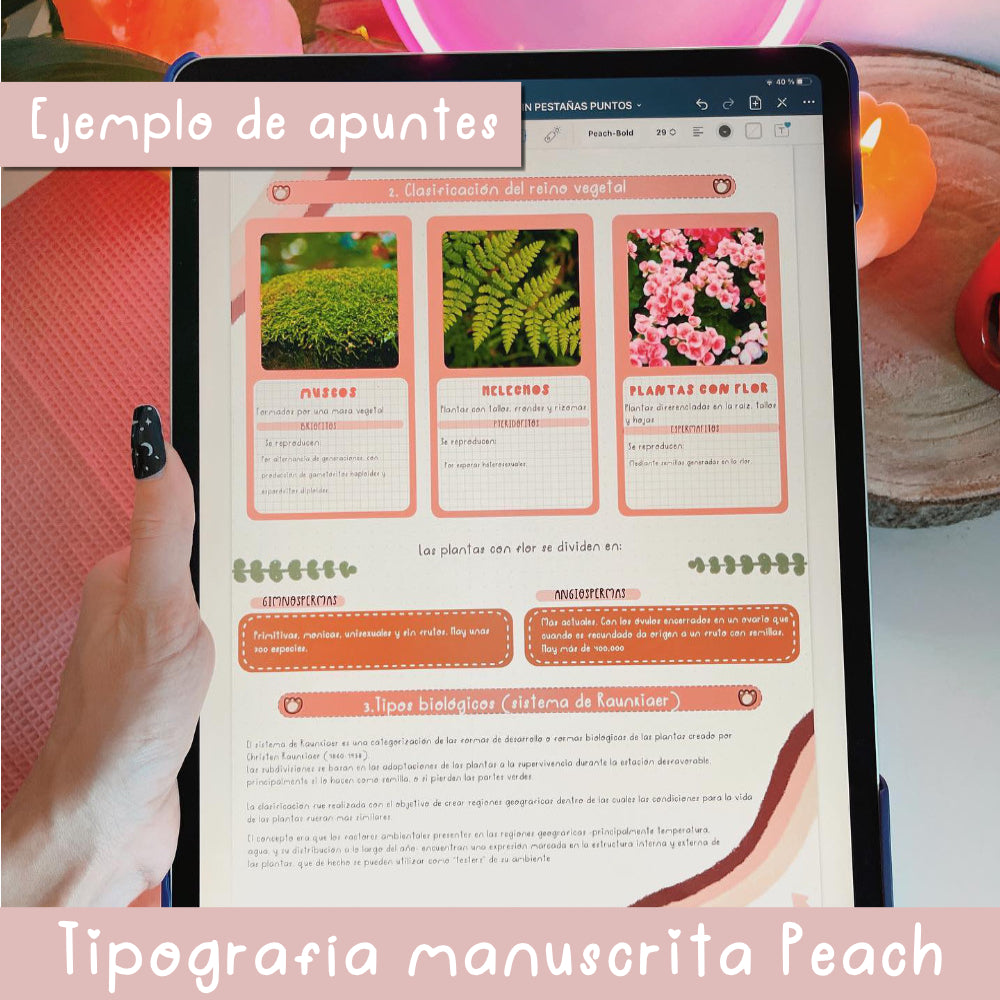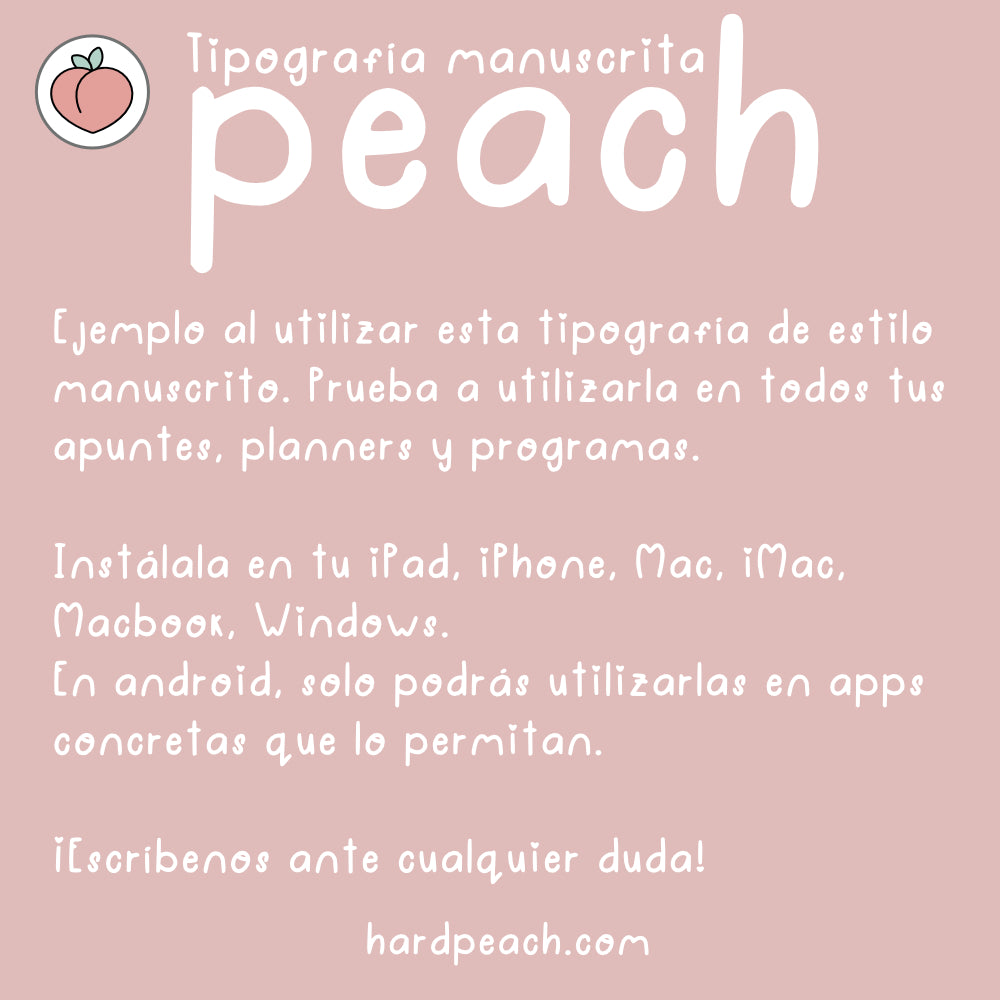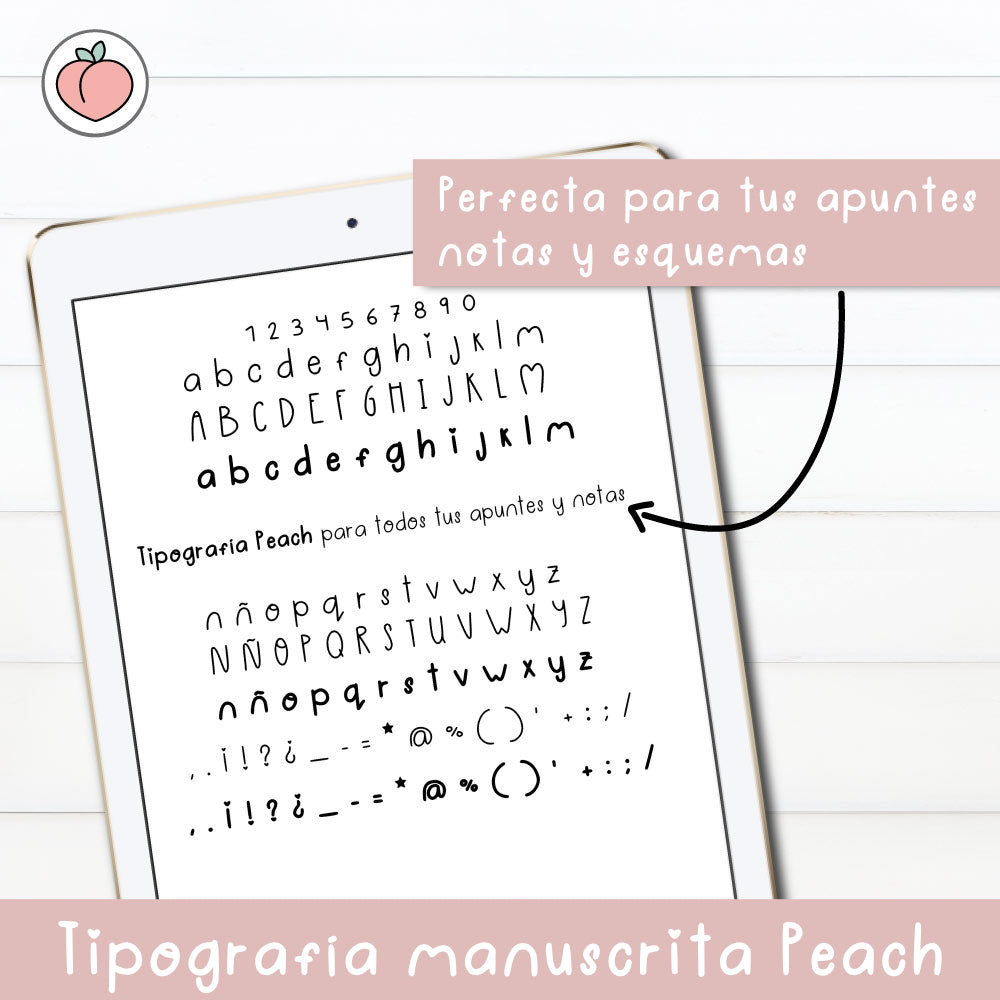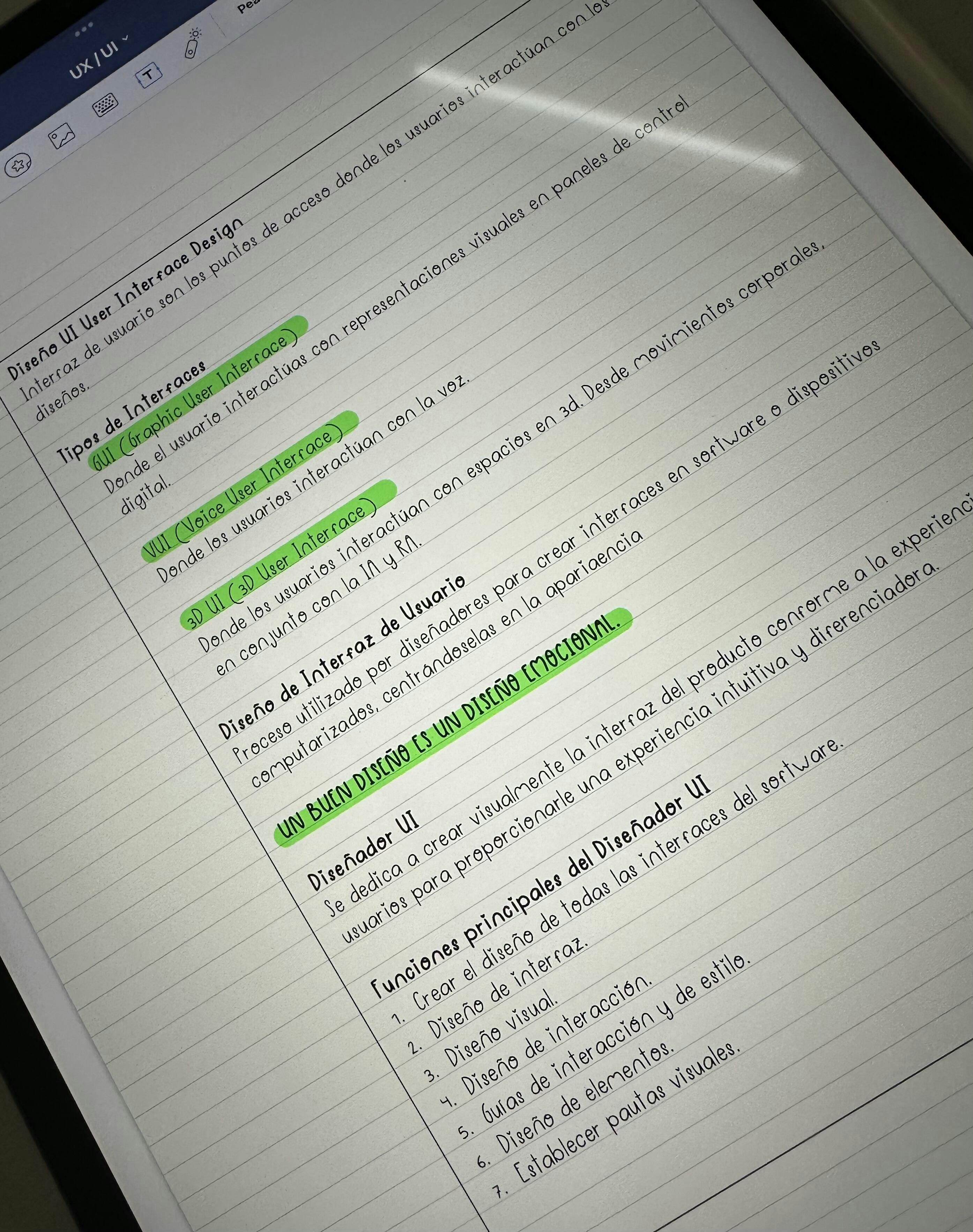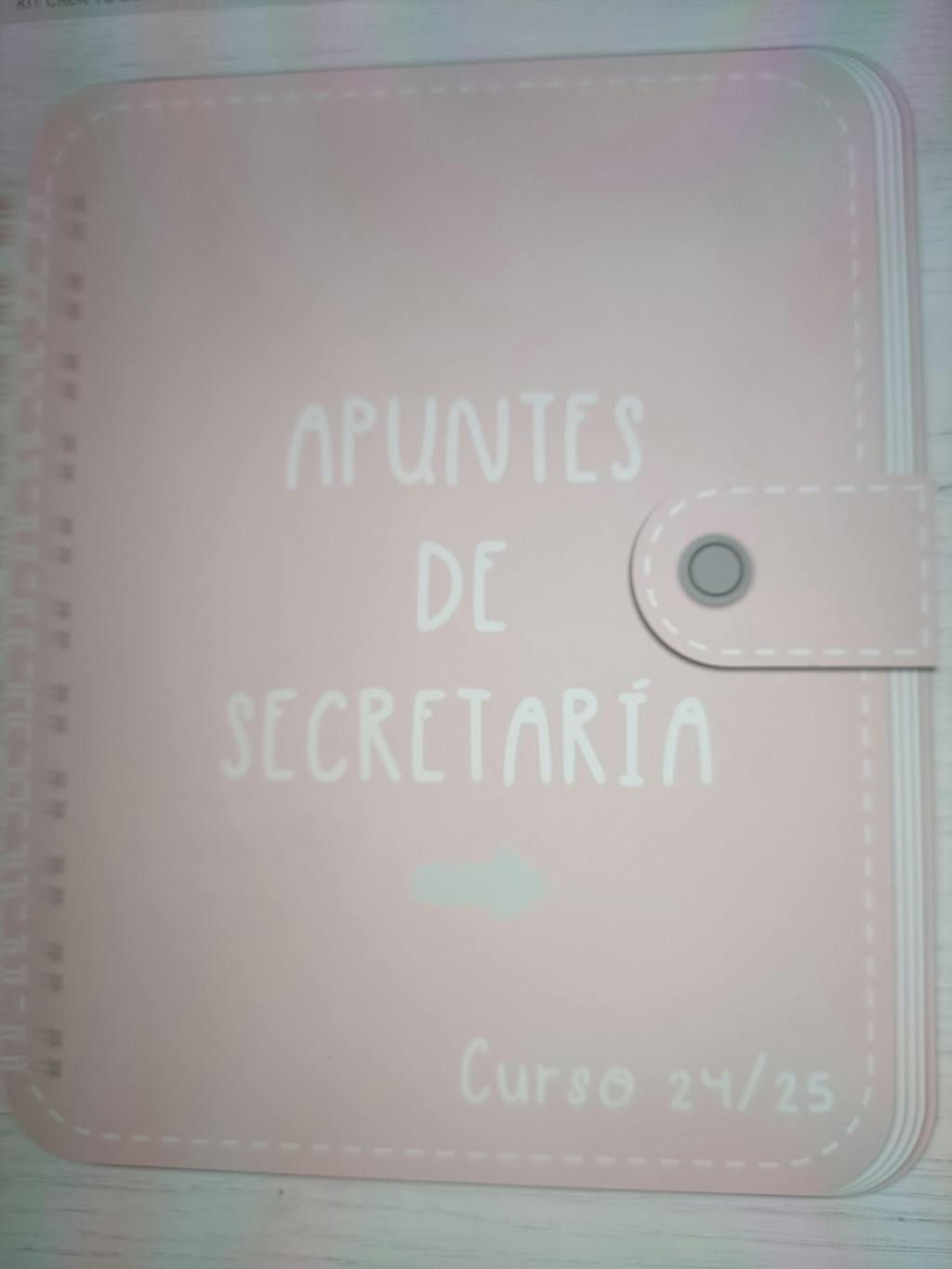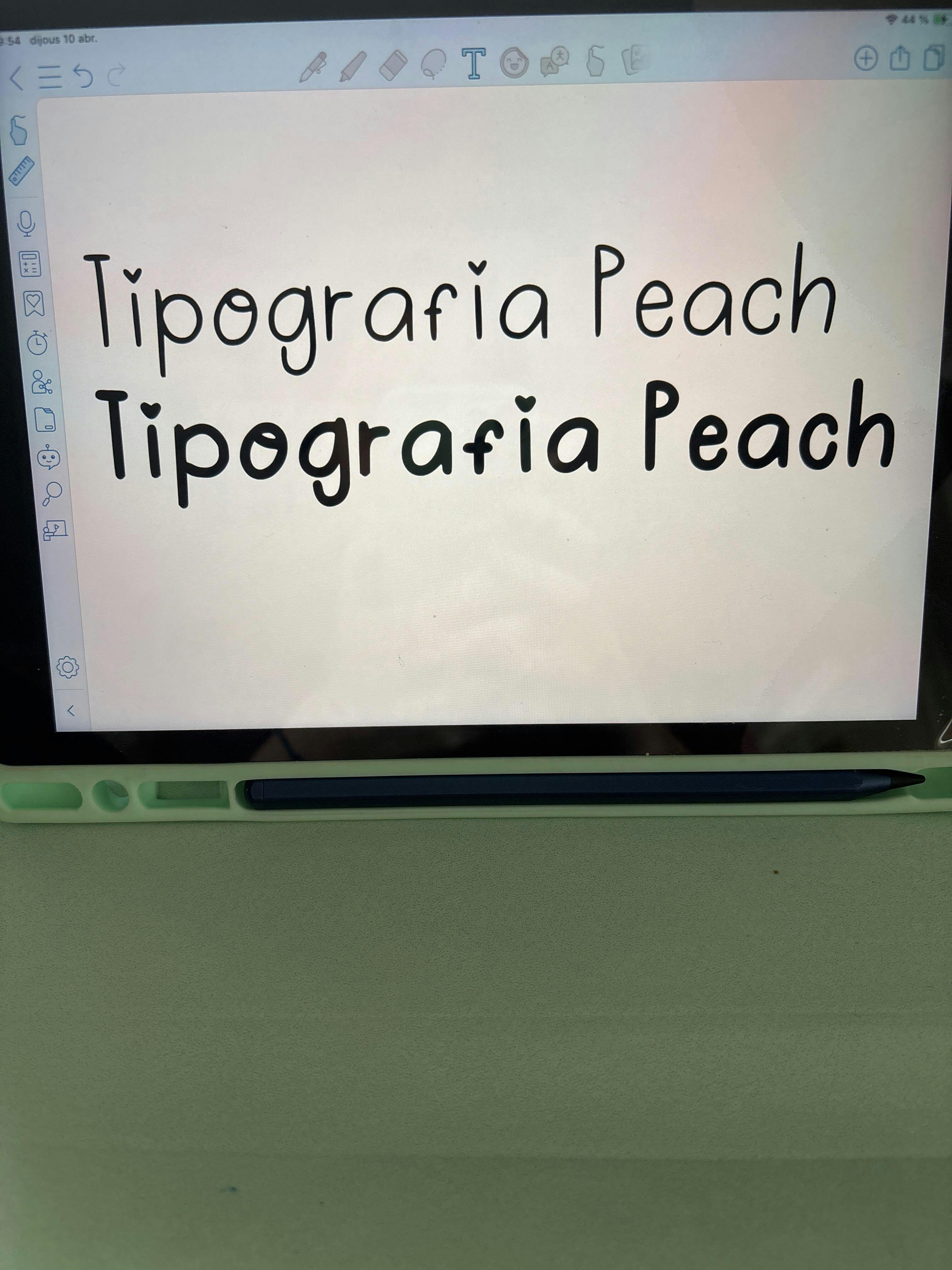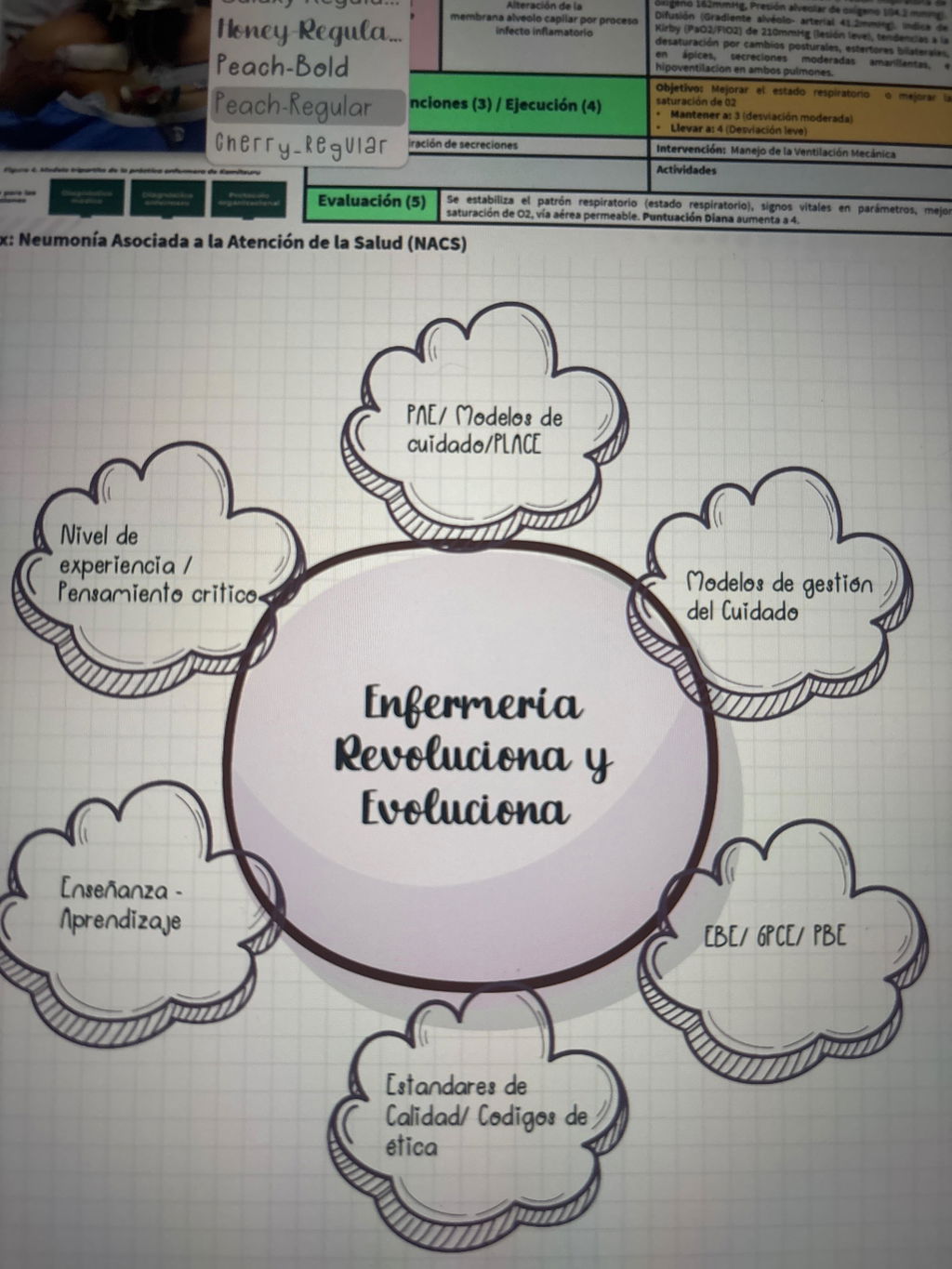
TIPOGRAFÍA MANUSCRITA PEACH | FUENTE ESCRITA A MANO
Descubre esta tipografía manuscrita Peach perfecta para darle un toque personal y único a tus apuntes, anotaciones, agendas, Bullet Journals y cualquier tipo de proyecto digital. Con ella podrás escribir de manera elegante y clara, tanto en títulos como en texto corriente, manteniendo un estilo uniforme y profesional en todas tus creaciones.
Ideal para estudiantes, profesionales, diseñadores o cualquier persona que quiera mejorar sus apuntes digitales, organizar tareas, hacer anotaciones creativas o agregar un toque estético a sus documentos y proyectos.
Esta tipografía está en Español incluye todos los caracteres principales, mayúsculas, minúsculas, números, vocales con tildes (español) y signos. Al estar en Español, no incluye algunas acentuaciones de otros dialectos o idiomas.
Los clientes elogiaron esta tipografía manuscrita por su diseño hermoso y versátil que mejora las notas y los documentos. Los compradores dijeron que es «práctica y hermosa», con letras claras y ordenadas, ideales para apuntes de estudio. Uno señaló las limitaciones de compatibilidad con Samsung Notes. Presenta detalles en forma de corazón en la letra «i». Fácil de descargar y usar con útiles tutoriales.